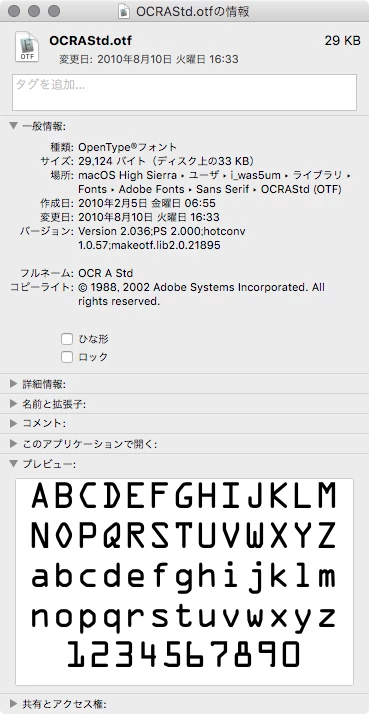
フォントについて質問です。『OCR-A』と『OCR-A Std』や『OCR-A REGURER』は同義でしょうか?
フォントについて質問です。
フォント許可リストに『OCR-A』がありますが、『OCR-A Std』や『OCR-A REGURER』も同義でしょうか?
ネットで調べて比較したところ同じフォントに見えますが・・・
フォント許可リストで『OCR-A』1234 と許可があるのは『OCR-A』系フォント全般の事でしょうか?
下記のドキュメントをご覧になったのですよね。
フォント許可リストで『OCR-A』1234 と許可があるのは『OCR-A』系フォント全般の事でしょうか?
違います。ここで注意すべきことは2つあります。
1.
そのリストにある「OCR-A」は、Adobeが提供している特定のフォントを指します。そもそも「OCR-A」は、現在はIOSの標準規格であり、昔から様々なところで同名フォントが作られてきました。
2.
名前が同じ、または似ているからといって全て許可では無いと思います。基本的にAdobeより販売・ライセンスされたものでは無いでしょうか。
OCRAStd.otf はCS4にバンドルされていたことがありますね。
OTF以前にはPostScript Type 1 Fontがありました。
OCRA Regular は多分Linotypeのものだと思いますが、ライセンスはメーカーに確認する必要があると思います。
フォントを作成したメーカー(ベンダー)が異なると、同じように見えても細部が異なるようです。
ですので、 ファッティGさんがあげられている『OCR-A』や『OCR-A Std』『OCR-A REGURER』についても「同じフォント」とは言い切れません。